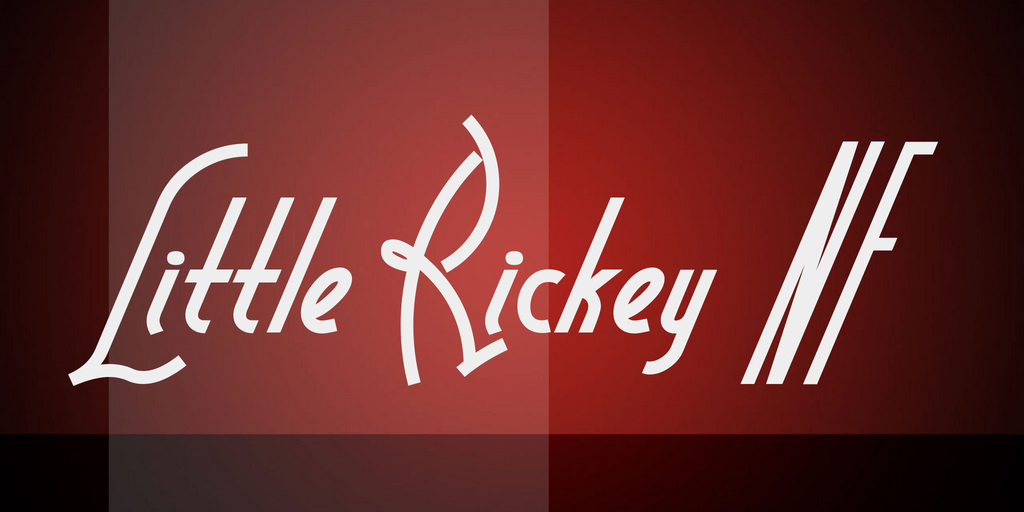
Esta fonte chamada Little Rickey NF é inspirada no traçado peculiar dos anos 1940 das embalagens de limão espanhol que apresentavam a Ricardo Llacer y Hijos, uma marca conhecida por suas laranjas deliciosas. Inspirada nos filhos nascidos em boa hora de Lucy e Desi, ela é um tipo de letra divertido e deslocado, perfeito para criar um visual chamativo e único. A fonte é ideal para aplicativos que exigem uma presença forte e destaca-se por sua estranha simetria e detalhes atraentes. É uma escolha ótima para marcas criativas ou qualquer projeto que deseje transmitir uma mensagem inovadora e divertida. Completando o conjunto, a fonte é perfeita para anúncios de publicidade, design gráfico dramático, cartazes e até mesmo aplicativos móveis que buscam destacar-se na multidão. Little Rickey NF é uma ótima escolha para quem busca um tipo de letra diferente, versátil e irresistivelmente atraente.